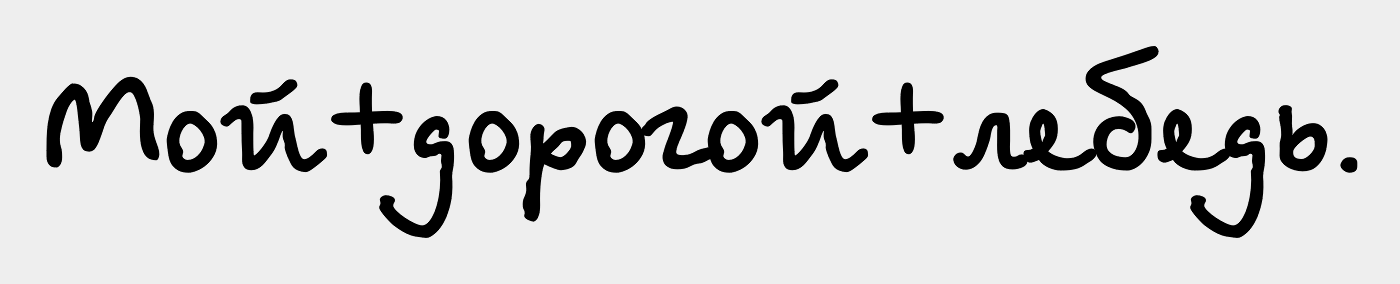
Suche ähnliche Schrift mit kyrillischen Zeichen
habe hier einen für uns erstellten Font. Kyrillische Zeichen sind in der Mache, aber wir suchen bis dahin eine Alternative.
Kennt ihr einen Font, der ähnlich ist, auch wenn das nicht so ganz leicht ist, weil es eine spezielle Font ist, die kyrillische Schriftzeichen hat?
Super viel durchgeschaut, aber nicht so fündig geworden. Lag aber, wie ich gemerkt habe, dass ich mich zu sehr an den westlichen Zeichen orientiert habe, die man halt als erstes sieht. Die Ford's Folly wirds auch nun werden. die Kyrillischen Zeichen passen da sehr gut. Die westlichen gehen da zum Glück etwas unter.
In ein paar Monaten wird unsere Schrift aber auch kyrillische Zeichen haben! :)